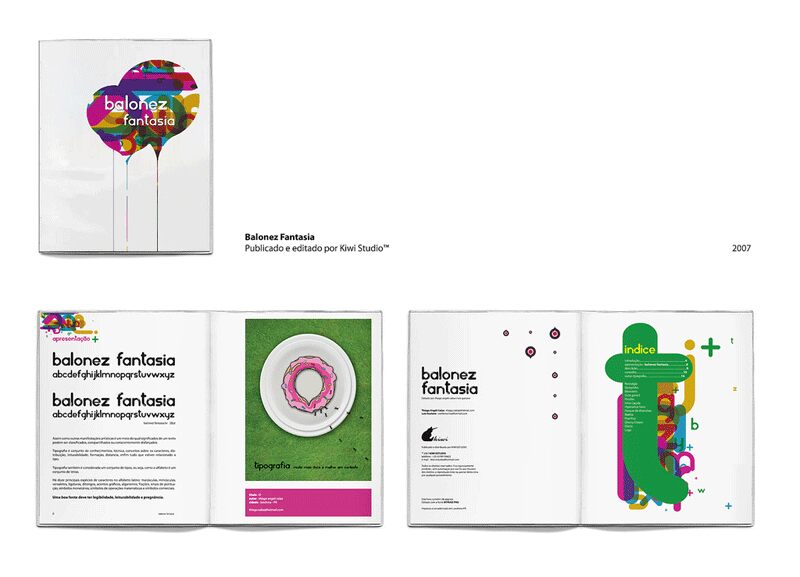
balonez fantasia br
Balonez Fantasia BR to darmowy, inspirowany balonami krój pisma typu display, charakteryzujący się obłymi kształtami oraz nowoczesnym, zabawnym charakterem. Szerokie, koliste litery, miękkie łączenia i drobne akcenty świetlne sprawiają wrażenie błyszczących, formowanych kształtów, a nie tradycyjnej typografii.
Jej wyrazista objętość nadaje zabawkowej, połyskującej estetyki opakowaniom słodyczy i materiałom skierowanym do dzieci. Wykorzystaj ten darmowy font w zaproszeniach na przyjęcia, plakatach festiwalowych, grafikach tytułowych do gier czy radosnych kampaniach w mediach społecznościowych, gdzie pękata geometria może świetnie współgrać z jasnymi ilustracjami i dynamicznymi układami.